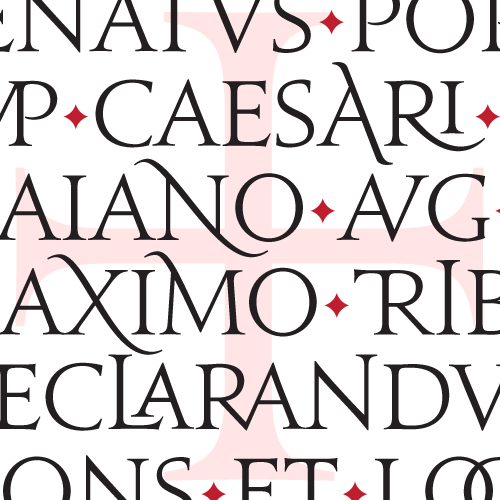
Alternativen zur Trajan
Eine professionelle Schrift soll halt auch noch gut aussehen, wenn man sie in Metergröße auf eine Straßenbahn oder einen LKW klebt.
Ich nutze Schriften halt nur in Größen im zweistelligen Bereich und hielt euch – zugegebenermaßen – für etwas überpenibel. Aber in LKW-Größe würde ich das sicherlich auch sehen.
gerade Font of the Day bei MyFonts:
Le Beaune Classic
Ich hab auch noch eine Schöne gefunden:
Die Jupiter von Canada Type:
H&FJ Requiem wurde ja bestimmt schon genannt :?